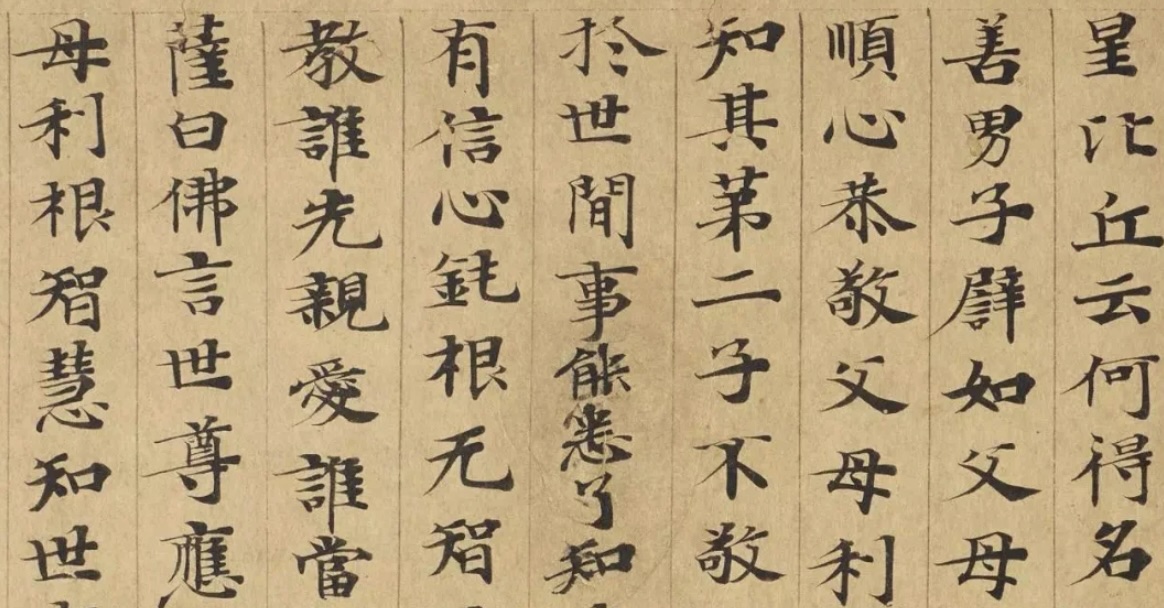
古籍印刷排版铅印墨迹字体
做国风、古籍复刻、文创设计的宝子们集合,谁懂找古籍风字体的痛?要么有版权风险,要么质感廉价,要么没有铅印的厚重、墨迹的温润,硬生生拉低古籍氛围感…耗时整理24款免费可商用古籍印刷排版铅印墨迹字体合集,全是古籍印刷、铅印、墨迹质感,涵盖木刻、活字、碑刻、毛笔墨迹等风格,兼顾古典底蕴与现代实用性,国风海报、古籍排版、文创设计、自媒体标题都适配,新手直接抄作业,不用再花时间筛选。
刻20世纪铅印古籍神韵,字面紧凑如铸铁,笔画边缘带手工雕琢的毛糙感,仿佛能嗅到油墨与纸张的陈旧气息,免费商用无压力,适配民国文献、老商标复刻。以《康熙字典》为蓝本,保留古籍方正骨架,笔画衔接处做现代化柔化,字面饱满如篆刻,适配海报标题、古籍复刻,屏幕显示清晰不生硬。
复刻民国铅印行书,笔画流畅不拖沓,自带旧时光油墨感,不生硬不刻意,适配古籍扉页、书信排版、国风标题,免费商用无版权风险。以明代木刻本《凌閔刻本》为蓝本,基于思源宋体改造,有木刻印刷的质朴感,书法韵味浓郁,简繁体支持完备,竖排横排都适配,适配古籍排版、文创设计。
适用:古籍复刻、国风海报、读书笔记、学习笔记封面、文创设计、复古手账……百搭又高级
思印宋
中华薪火体
仲春仿宋
纳米老宋
汇文明朝体GBK
汇文仿宋
汇迹正楷
汇文港黑
寒蝉活仿楷
寒蝉活仿宋
寒蝉活楷体
寒蝉活宋体
寒蝉活黑体
黄令东齐伋体
黄令东齐伋复刻
香萃打字机体
润植家康熙字典美化体
新愚公沧桑体
新愚公迷茫体
汇文筑地五号明朝体
大正略字
大正活字
南北词宫谱宋体
ORADANO Mincho 明朝体